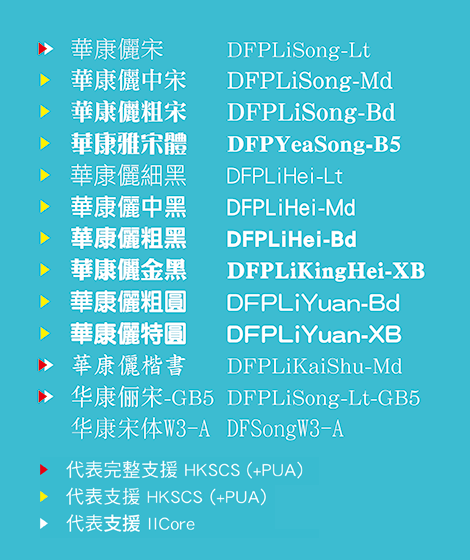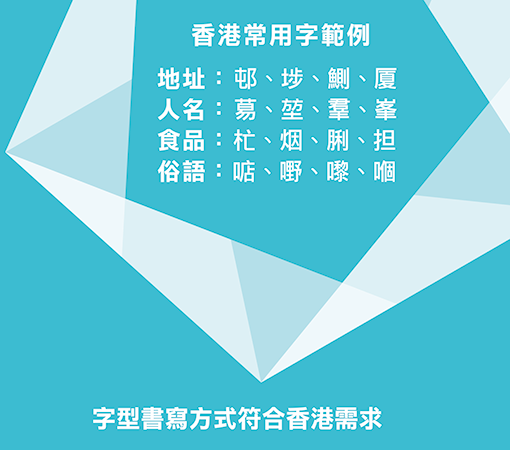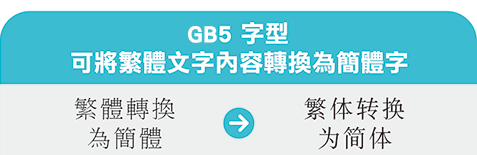
全面採用 Unicode 編碼
書寫方式更符合香港需求
自動搭配對應的英文字型最佳中英文混排效果
香港有頗多中文字與現有的電腦中文字寫法不盡相同,華康為了充份照顧香港用戶的需要,將所有字型修訂至符合香港常用的書寫方式。
香港增補字符集 HKSCS 有兩套編碼方案,一套適用 ISO 10646 國際編碼標準平台,另一套適用於大五碼系統,「香港靚字集 X1」的中文字符已包括以上兩套編碼方案在內;除了支援 HKSCS 規格以外,更同時支援舊版 GCCS 規格,確保用戶新舊文件都不會缺字。
簡體字型幫助用戶將文件檔案進行繁簡轉換,沒有簡體字碼的位置會以繁體字自動填上,解決中港兩地文件往來的問題。 從內地送來的 GB 碼文件檔,亦可利用簡體字型在 Unicode 與 Big-5 視窗環境下即時閱讀及列印。
國際標準 International Ideographs Core (IICORE) 表意文字子集包含 9,810 個字符。適合用於記憶體容量、輸入/ 輸出能力有限的設備。「香港靚字集 X1」方便電腦用戶與小型通訊裝置交換訊息。
「香港靚字集 X1」所有字型都附有風格完全對應的英文字型,並有 Proportional spacing 調和字格式,可做出最佳的中英文字混排效果。